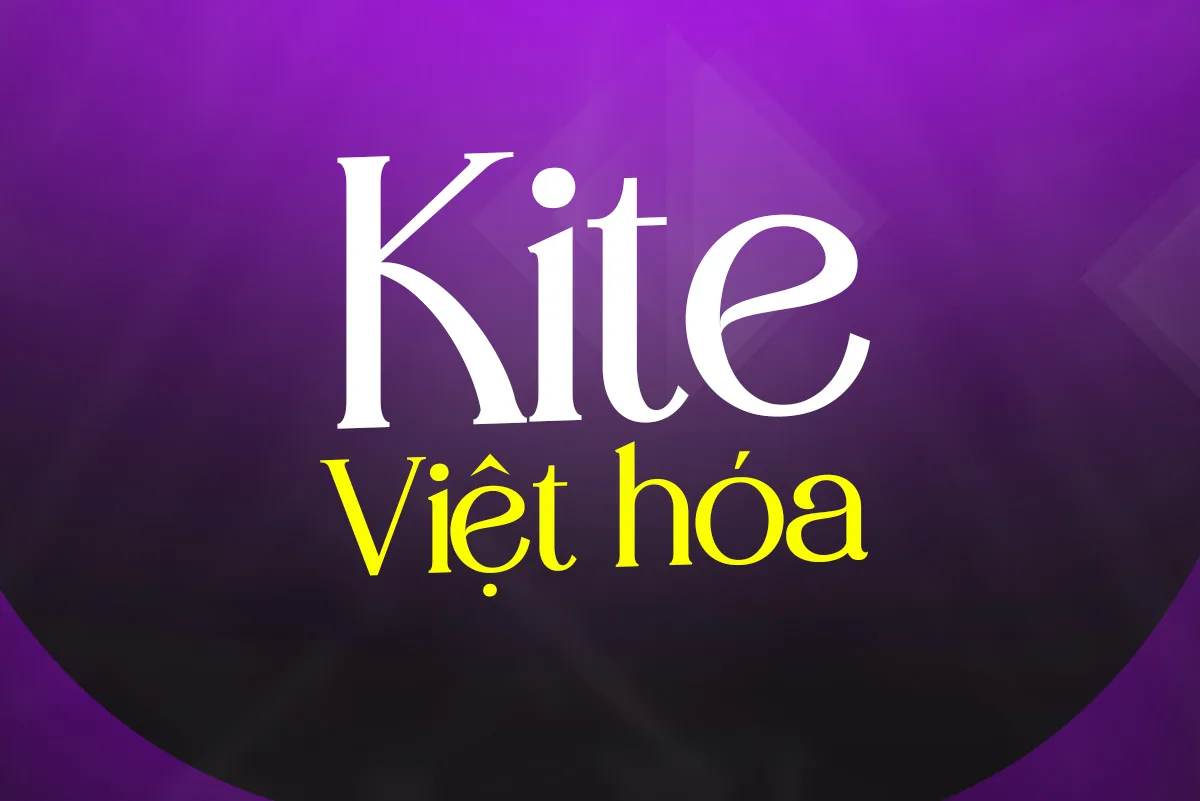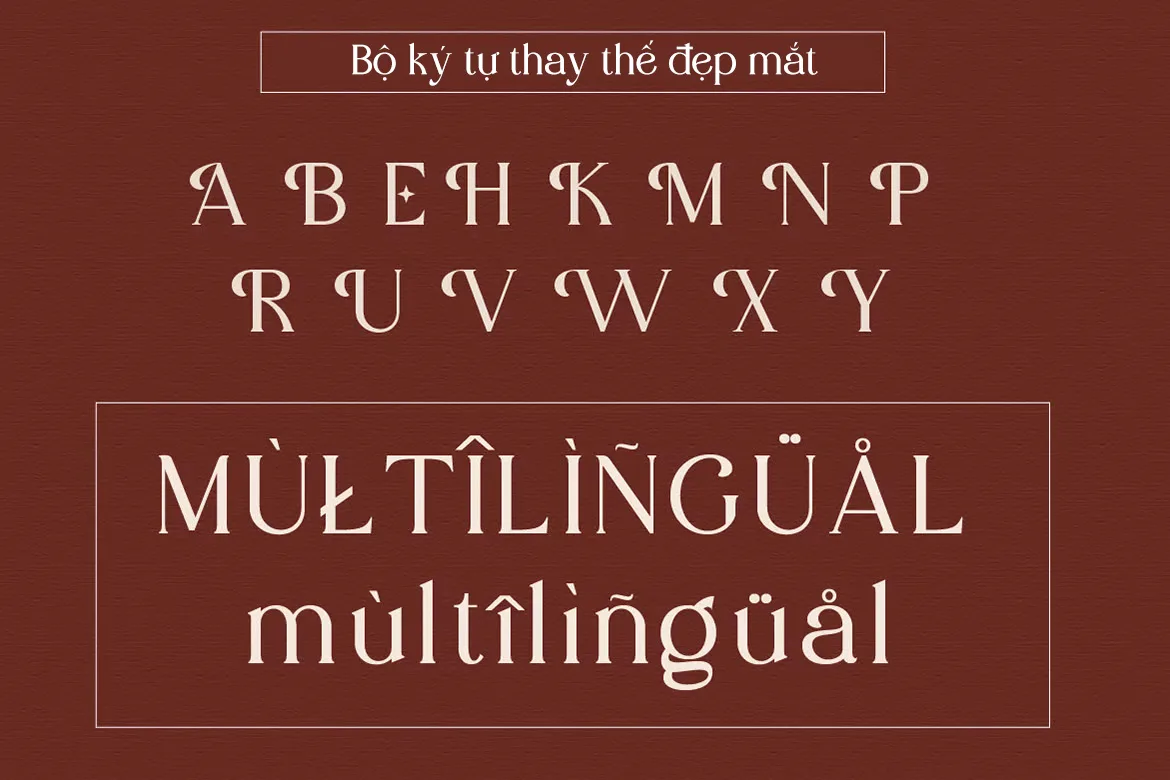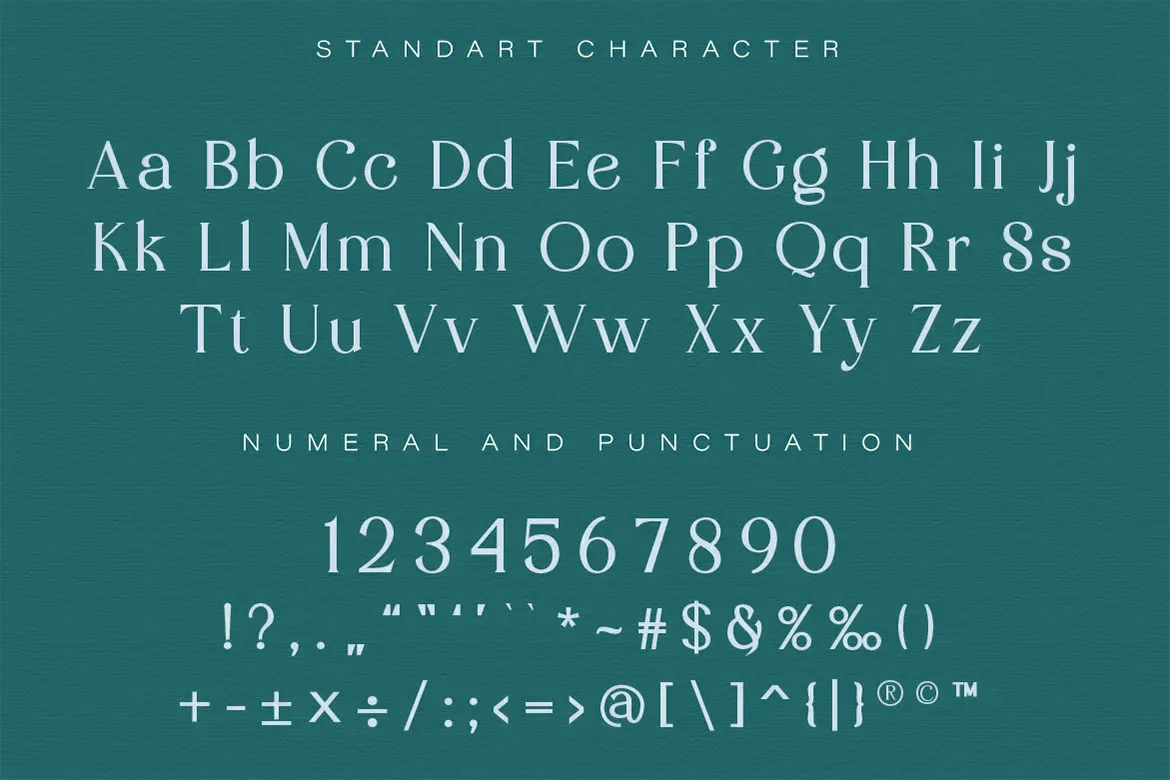
DVN Kite Việt hóa – Font serif thanh lịch, hiện đại với bộ ký tự mở rộng
DVN Kite Việt hóa là một kiểu chữ serif mang hơi hướng hiện đại kết hợp cổ điển, với phong cách sang trọng, thanh thoát và đậm chất sáng tạo. Font sở hữu các chữ hoa thay thế (alternates) độc đáo, giúp dễ dàng tạo điểm nhấn cho tiêu đề, logo hoặc bìa ấn phẩm. Bộ font hỗ trợ đầy đủ tiếng Việt, dấu câu, chữ số và nhiều ngôn ngữ quốc tế. DVN Kite phù hợp cho các dự án thiết kế cao cấp như thương hiệu mỹ phẩm, thời trang, editorial, thiệp mời hay các sản phẩm mang tính nghệ thuật.